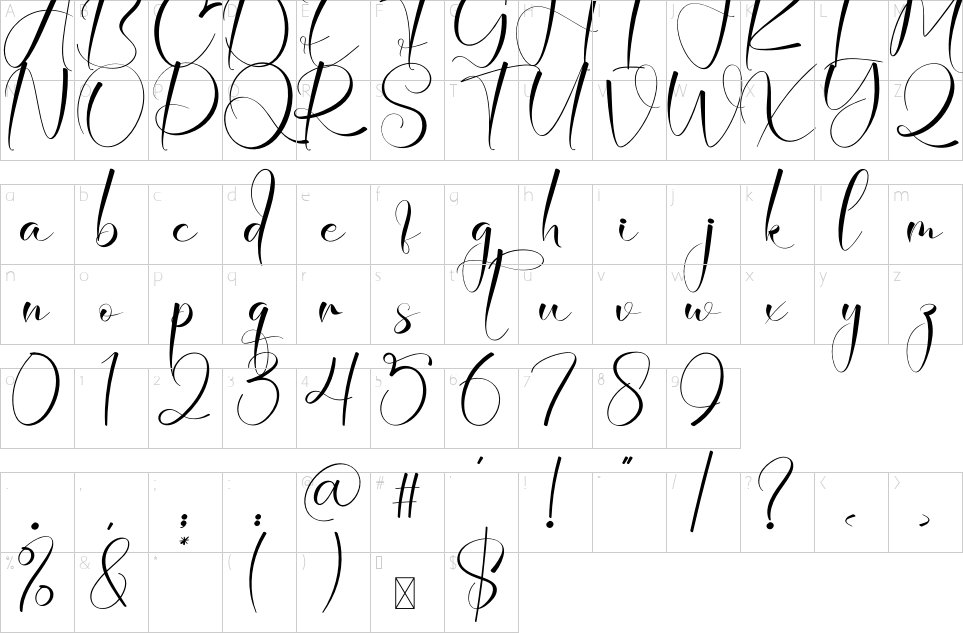
A fonte Margaretta Signature é uma seleção de letras única e moderna, projetada pelo designer scratchones. Esta fonte para Windows e Mac é uma escolha perfeita para quem busca uma linguagem elegante e fácil de ler. Com sua designação ideal para escritas digitais, Margaretta Signature é uma excelente opção para marcas, banners e qualquer tipo de design que exige uma aparência limpa e sofisticada. A fonte já foi baixada 482 vezes, demonstrando sua popularidade entre designers e estilistas. Descarregue agora Margaretta Signature para tornar seu design ainda mais profissional.